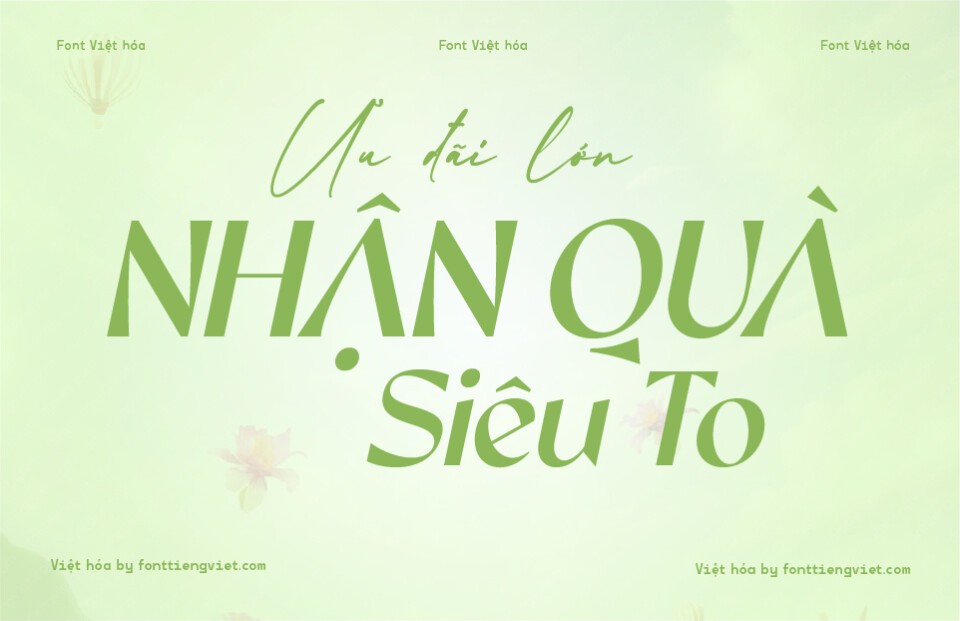
Font Việt hóa 1FTV VIP Sooner Iltalic
Trong thế giới đồ họa sáng tạo ngày nay, việc lựa chọn một bộ Font Miễn Phí chất lượng luôn là ưu tiên hàng đầu của các nhà thiết kế và học sinh sinh viên. Một trong những cái tên đang gây chú ý chính là Font Việt hóa 1FTV VIP Sooner Iltalic. Đây là một phông chữ mang phong cách hiện đại, thanh lịch và đầy cá tính. Với đường nét nghiêng tinh tế, bộ font này không chỉ giúp nội dung trở nên nổi bật mà còn mang lại cảm giác chuyển động mượt mà cho các ấn phẩm truyền thông. Việc sở hữu một bộ font đã được Việt hóa hoàn chỉnh giúp người dùng dễ dàng thể hiện ý tưởng mà không lo lỗi font hay thiếu ký tự đặc trưng trong tiếng Việt.
Khám phá đặc điểm nổi bật của Font Việt hóa 1FTV VIP Sooner Iltalic
Font Việt hóa 1FTV VIP Sooner Iltalic được cộng đồng thiết kế tại Việt Nam đánh giá cao nhờ vào cấu trúc chữ đồng nhất và khả năng hiển thị sắc nét trên nhiều thiết bị. Kiểu dáng Italic (nghiêng) của phông chữ này không quá gắt, tạo ra sự mềm mại nhưng vẫn giữ được độ chuyên nghiệp cần thiết. Điều này rất quan trọng khi bạn muốn nhấn mạnh thông điệp trong các tiêu đề hoặc các đoạn trích dẫn quan trọng. Độ tương phản giữa các nét thanh và nét đậm được căn chỉnh tỉ mỉ, giúp văn bản dễ đọc ngay cả ở kích thước nhỏ.
Tính ứng dụng linh hoạt trong học tập và công việc
Đối với các bạn học sinh và giáo viên, Font Việt hóa 1FTV VIP Sooner Iltalic là công cụ đắc lực để trình bày các bài thuyết trình PowerPoint hoặc thiết kế báo tường số. Sự hiện đại của phông chữ giúp bài học trở nên sinh động và thu hút sự chú ý hơn. Trong lĩnh vực quảng cáo, phông chữ này thường xuyên xuất hiện trên các banner, poster phim hoặc bìa sách nhờ vẻ ngoài thời thượng. Khả năng tương thích tốt với các phần mềm đồ họa phổ biến như Adobe Photoshop, Illustrator hay Canva giúp người dùng tối ưu hóa quy trình làm việc một cách hiệu quả nhất.
Hướng dẫn sử dụng Font Việt hóa 1FTV VIP Sooner Iltalic hiệu quả
Để phát huy tối đa vẻ đẹp của Font Việt hóa 1FTV VIP Sooner Iltalic, bạn nên kết hợp nó với các phông chữ không chân (Sans-serif) dạng đứng để tạo sự cân bằng thị giác. Việc sử dụng quá nhiều chữ nghiêng trong một đoạn văn dài có thể gây mỏi mắt, vì vậy hãy ưu tiên dùng bộ font này cho các câu khẩu hiệu (slogan) hoặc tên thương hiệu. Ngoài ra, việc điều chỉnh khoảng cách giữa các chữ cái (kerning) cũng giúp bố cục tổng thể trở nên hài hòa hơn. Đừng ngần ngại thử nghiệm với các màu sắc tương phản để làm nổi bật những đường cong đặc sắc của bộ chữ này.
Lý do nên lựa chọn font chữ đã Việt hóa
Sử dụng các phiên bản Việt hóa như Font Việt hóa 1FTV VIP Sooner Iltalic giúp bạn tránh được những rắc rối về hiển thị dấu câu. Các ký tự đặc biệt như “ă”, “ê”, “ơ” hay các dấu thanh đều được chăm chút kỹ lưỡng về mặt thẩm mỹ, đảm bảo không bị lệch dòng hay sai lệch hình dáng so với các chữ cái Latin cơ bản. Đây là yếu tố sống còn để duy trì sự chuyên nghiệp trong các bản thiết kế dành cho thị trường Việt Nam.